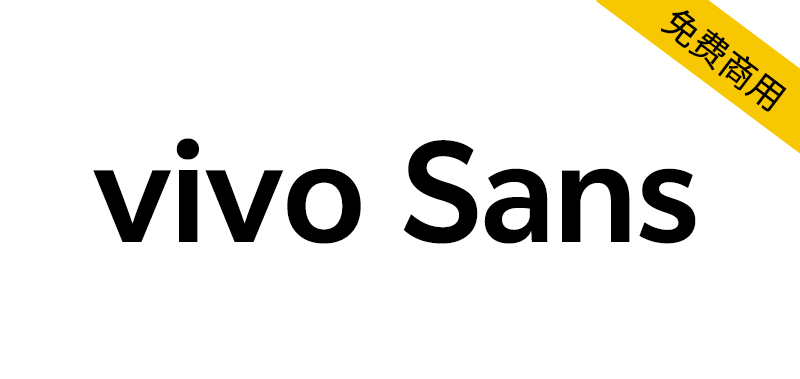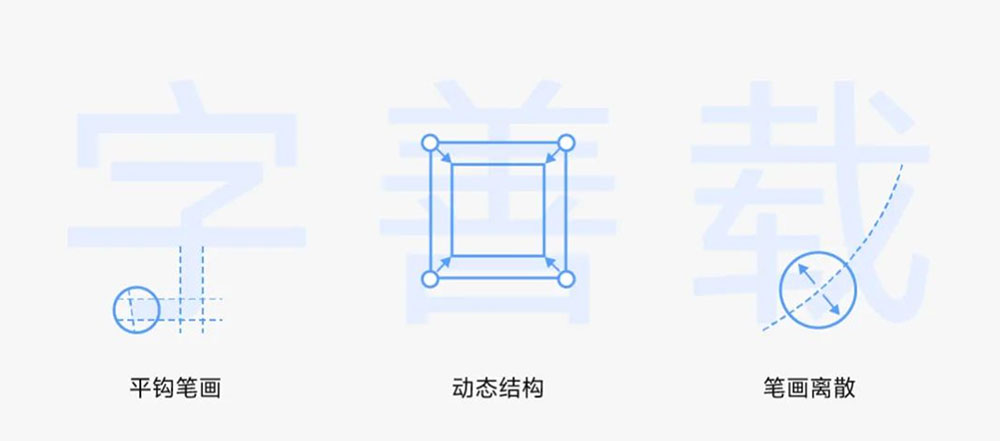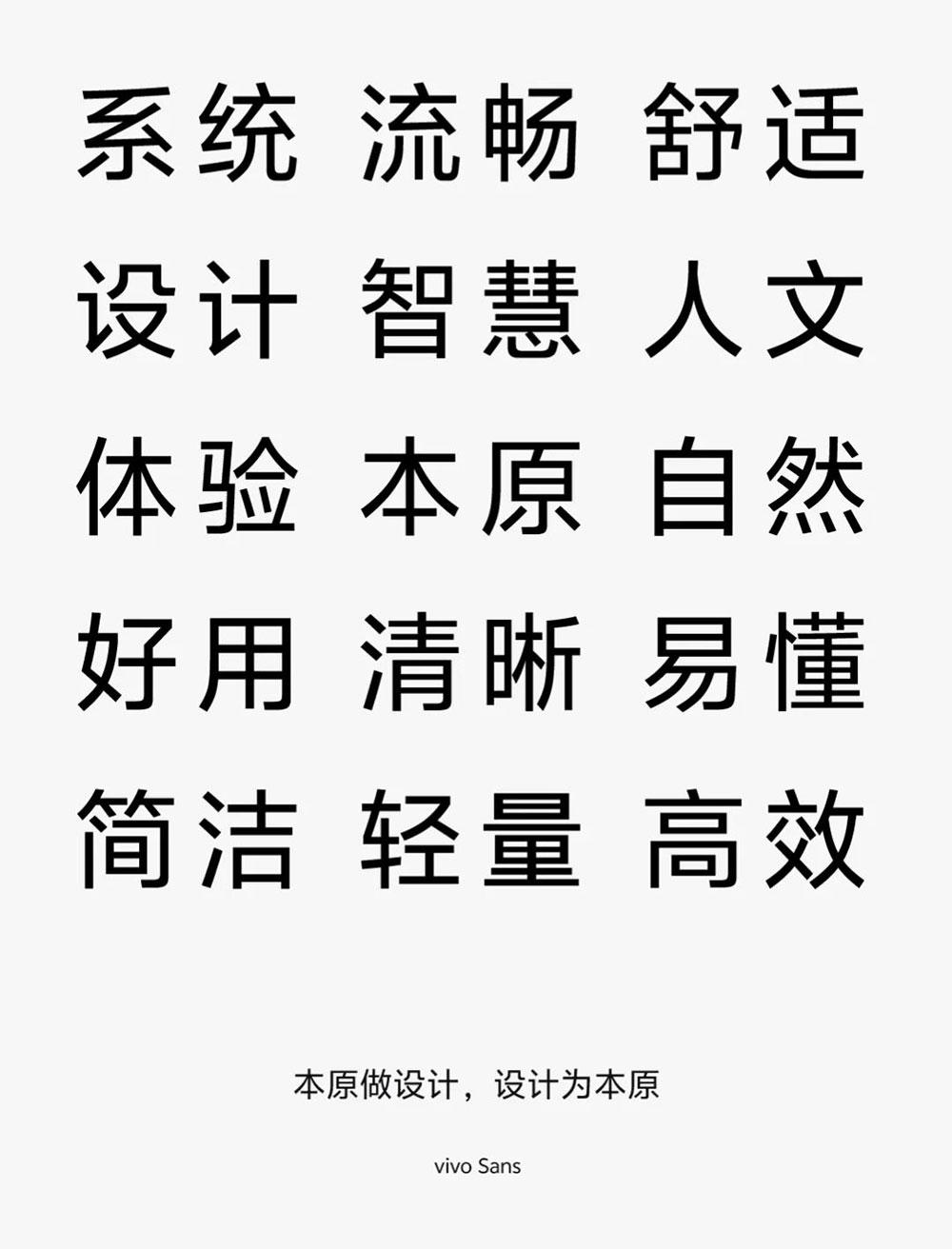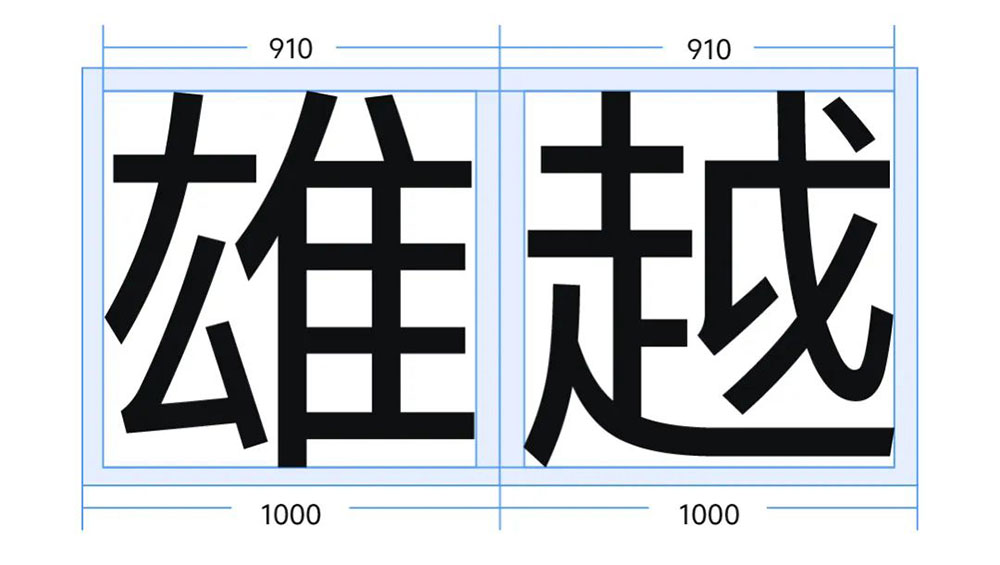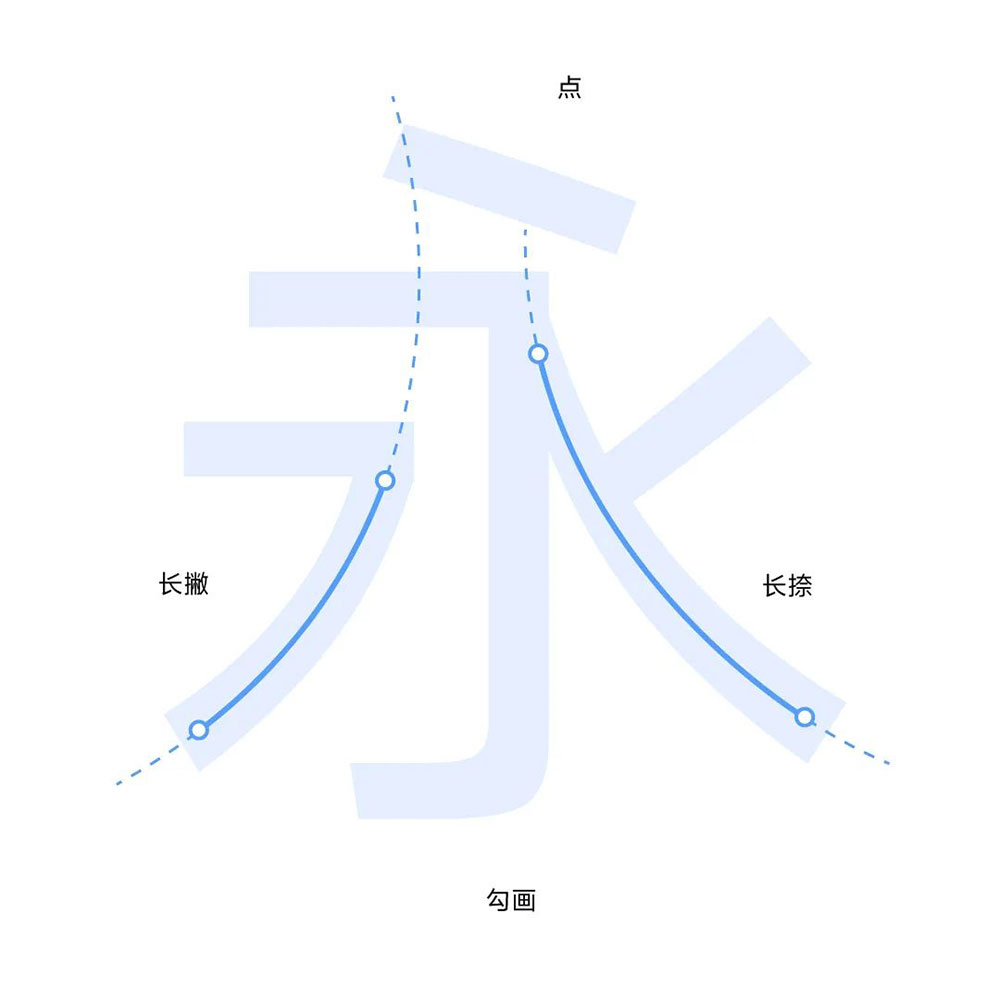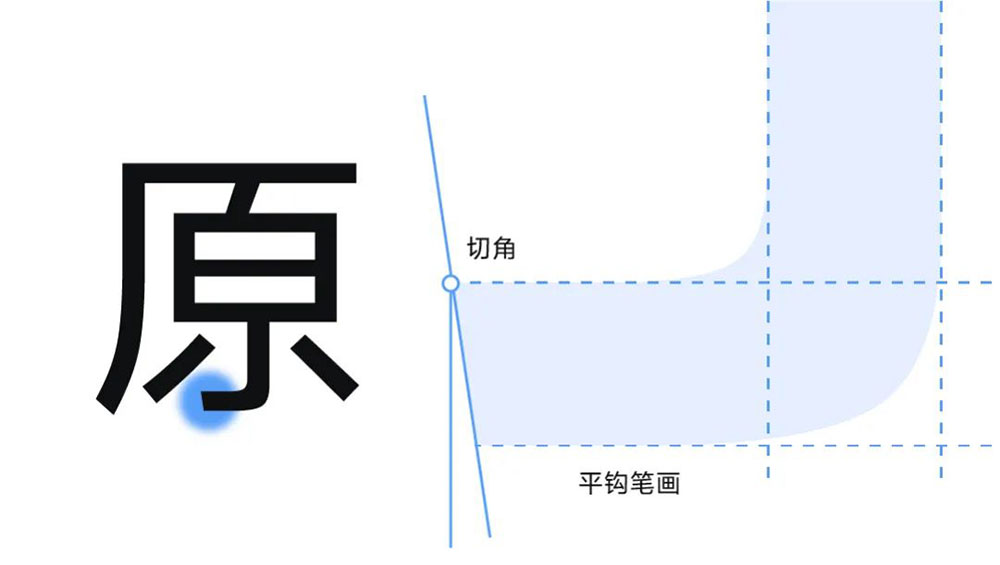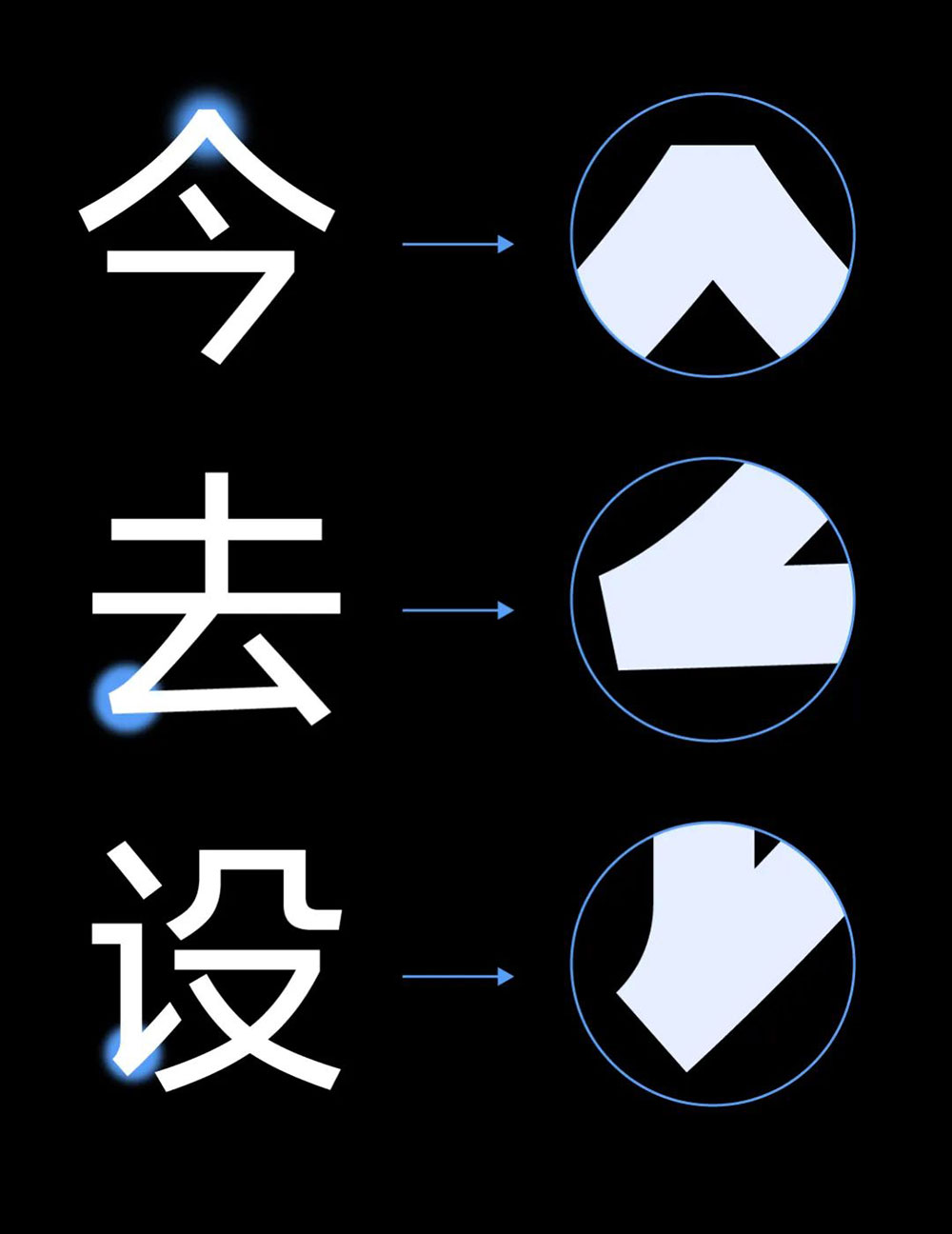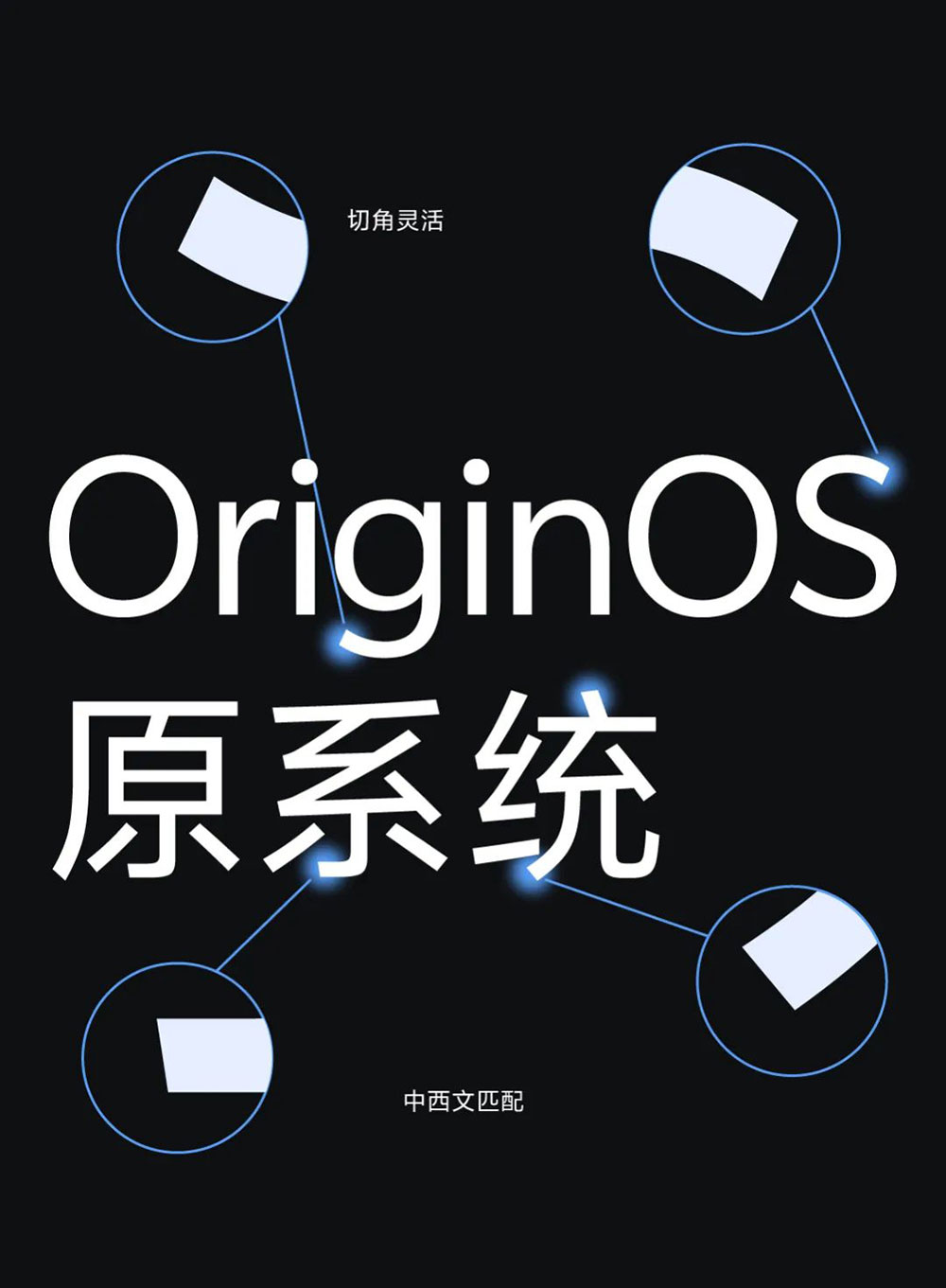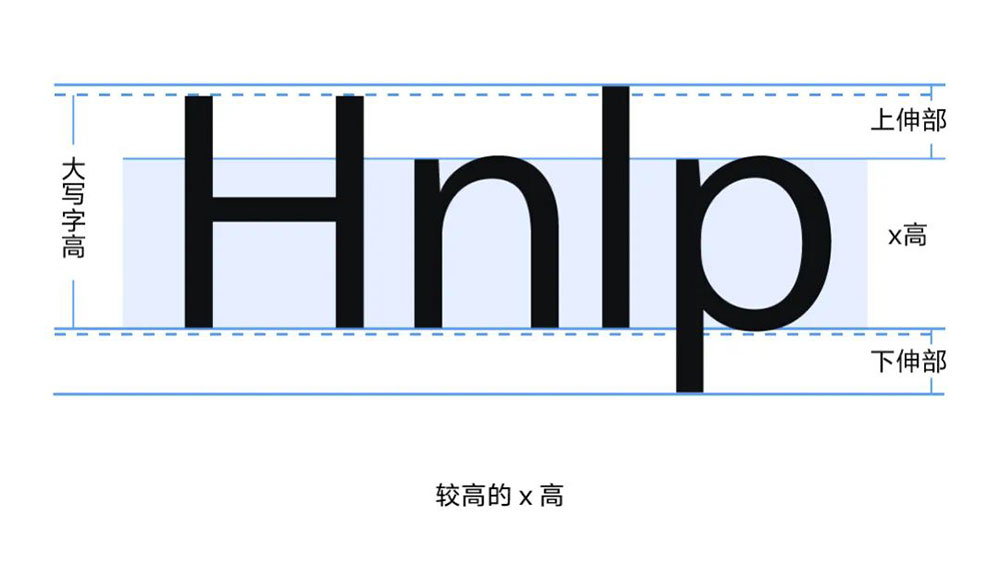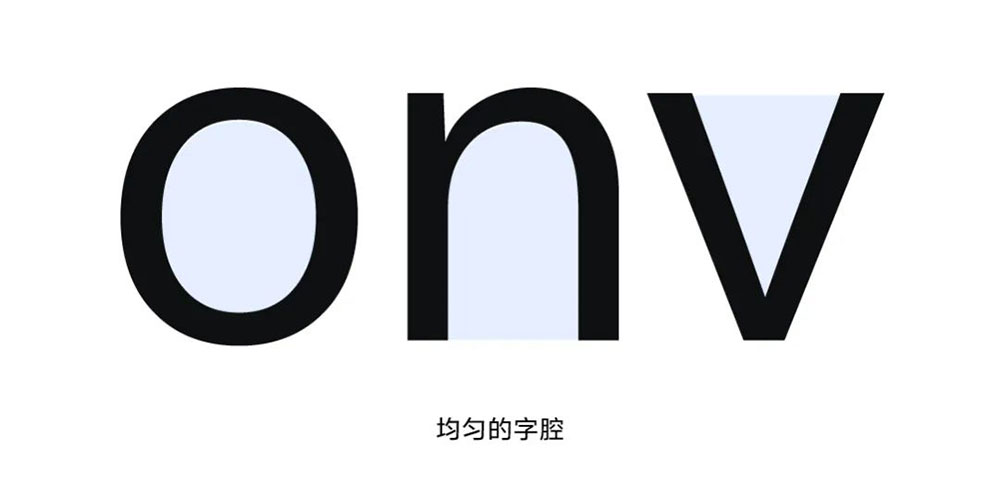
2023年vivo开发者大会上,vivo携手方正字库,带来全新品牌定制字体——vivo Sans。2024年10月,vivo宣布vivo Sans字体正式面向全社会开放免费商用,欢迎下载使用。vivo Sans字体还获得了美国IDEA设计大奖组委会所授予的2024 UI 设计类银奖。
vivo Sans中文字库已扩展至9.6万字的超大字符集,覆盖繁体字、古汉字以及大量生僻字,并支持人名、方言、典籍等多场景的文字使用和传承,还增加了希腊文和西里尔文书写系统,覆盖多达26种语言。
vivo Sans字体由vivo与方正字库携手设计,基于传统文字的美学原则,同时充分考虑数字显示的特点,力求为用户带来更加自然舒适的阅读体验。vivo Sans设计核心回归文字的本质,注重简洁与易读性,摒弃过多的装饰细节,专注于精细的结构优化。通过这样的设计,不仅提供清晰易读的文字效果,还能让用户更好地专注于内容本身,提升整体的阅读体验。
字体结构:vivo Sans采用91%的大字面率,注重提升文字的易读性和识别度,尤其适合长时间阅读。通过均匀的字间布白、合理的部件比例以及巧妙的笔画避让设计,字体在视觉上更加协调,同时帮助减少阅读疲劳,在全场景提供流畅、舒适的阅读体验。
曲线设计:为了确保文字在不同屏幕分辨率和尺寸下的阅读效果得到优化,vivo与方正设计团队特别注重整体字形的质感与美观度。vivo Sans的笔画处理融入了适度的书写特征,既保持了现代感,又赋予了字体独特的人文气息。连续平滑的曲线设计使字体更具柔和的视觉韧性,增强了其适应不同场景的表现力。
笔画设计:vivo Sans的勾画采用趋平式设计,笔画线条更贴合屏幕像素的分布特性,提升了在数字设备上的表现力。笔画末端采用简洁利落的直线切角设计,并根据不同笔画位置灵活调整切线角度。这样的平钩笔画与智慧切角处理,不仅确保了字体的舒适阅读体验,还赋予了它独特的视觉个性,使其在众多黑体中脱颖而出,呈现出鲜明的辨识度。
简约设计:作为vivo全新品牌定制字体,vivo Sans在设计中删繁就简,力求为用户提供更高效的阅读体验。部分笔画在相交和折笔处采用了减省和去锐处理,使字体在风格上呈现出现代与简洁特质的同时,显著提升了识读效率,使用户能够更加轻松地获取信息。
vivo Sans的西文字体延续了中文的设计风格和笔触细节,既保留了现代化的外观设计,又确保在不同角度、大小和距离下具有出色的易读性。为适应手机系统中不同场景和页面的西文字符显示需求,设计团队深入考虑了特征优化,无极的西文变体设计,确保字体在各类应用环境中都能灵活展现,达到最佳的视觉效果。
vivo Sans的西文采用简洁现代的无衬线设计,字体「x高」较高,字腔均匀开阔,呈现出充盈挺括、饱满舒张的视觉效果。字符宽度设计协调、字间距节奏均匀,整体风格传递出稳重平衡、中性普适的风格特质,适用于多种场景和使用需求。